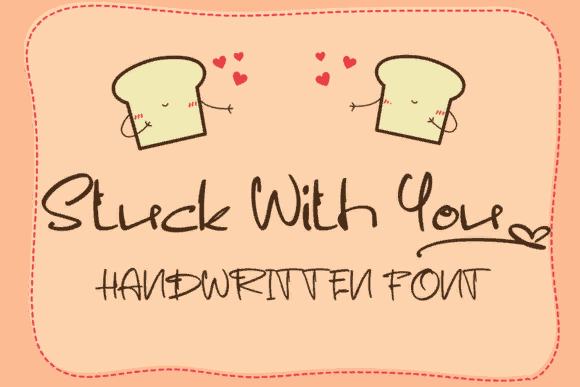
Stuck With You
- это милый и дружелюбный рукописный шрифт.
Его естественный и уникальный стиль делает его невероятно подходящим для большого количества дизайнов.